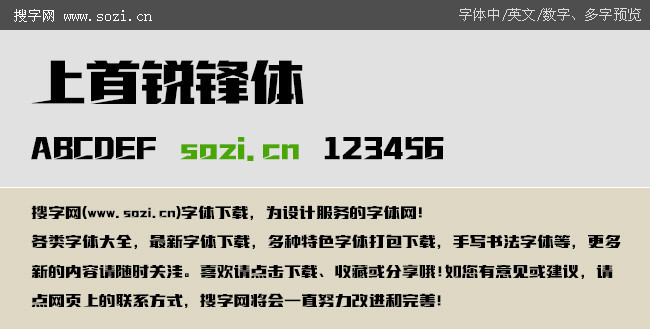
上首銳鋒體
搜字網(wǎng)給大家提供一款上首銳鋒體中文字體下載,上首銳鋒體字體筆畫采用規(guī)整的幾何圖形做法,底部橫線采用鋒銳的三角形,在方正之中給人一種鋒銳和力量的感覺。筆畫整體粗細(xì)均勻,字體方正飽滿。適用于搭配標(biāo)志、廣告標(biāo)語、商業(yè)廣告等廣告設(shè)計。